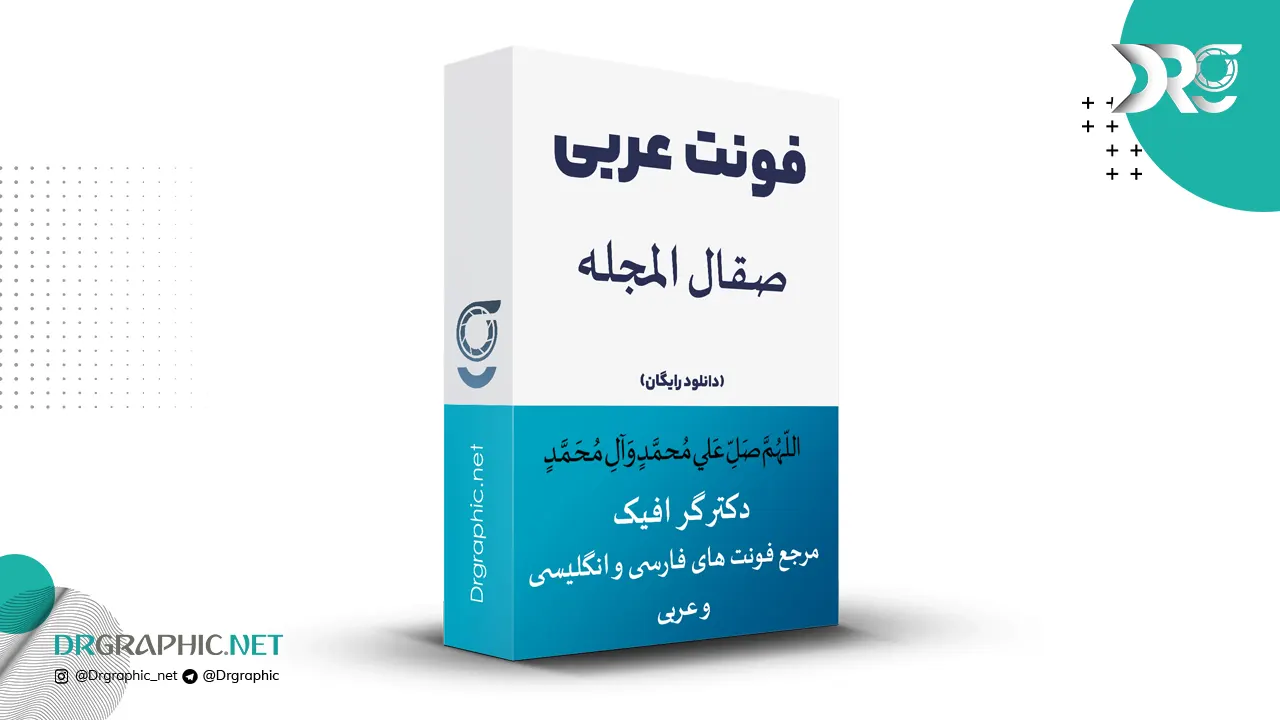
دانلود فونت عربی صقال المجله Sakkal Majalla
طراحان وب سایت و گرافیست های خلاق می توانند از این فونت زیبا در طراحی پروژه های مذهبی، اسلامی خود استفاده کنند.
فونت های عربی به خاطر شباهت زیادی که به فونت های فارسی دارند (فاقد چهار حرف: گ، چ، پ، ژ) می توانند کمبود تنوع فونت های فارسی را تا حدودی جبران نموده و مورد استفاده طراحان در طراحی ها قرار بگیرد.